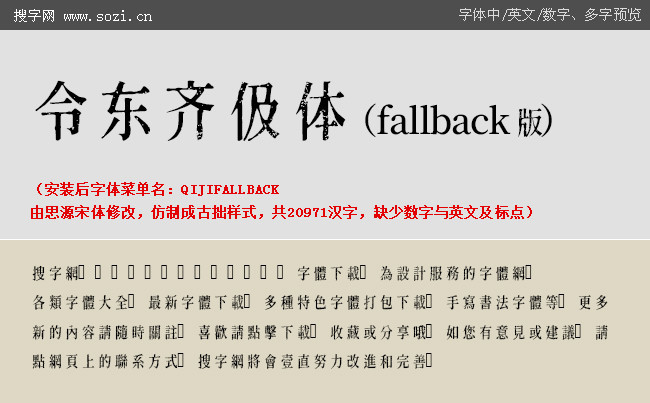
令東齊伋體(fallback版)
搜字網(wǎng)給大家提供一款令東齊伋體(fallback版)中文字體下載,是一套古籍刻本字體,摘錄自明代古籍《李長吉歌詩》和《淮南鴻烈解》,采用半自動計(jì)算機(jī)視覺和OCR制作而成的一款字體,所以缺少英文、數(shù)字及標(biāo)點(diǎn)。令東齊伋體共有三個版本,分別是:qiji.ttf:僅有古籍原字,共5916字符;qiji-fallback.ttf:完全由思源宋體修改,仿制成古拙樣式,共20971漢字;qiji-combo.ttf:古籍原字+補(bǔ)充的思源宋體(即古籍中沒有的字)。 其筆畫風(fēng)格書法特征濃郁,比常規(guī)的明朝體更具韻律感,富有人文氣息。而且可以免費(fèi)商用!適合海報(bào)設(shè)計(jì)、包裝設(shè)計(jì)等宣傳廣告等應(yīng)用。